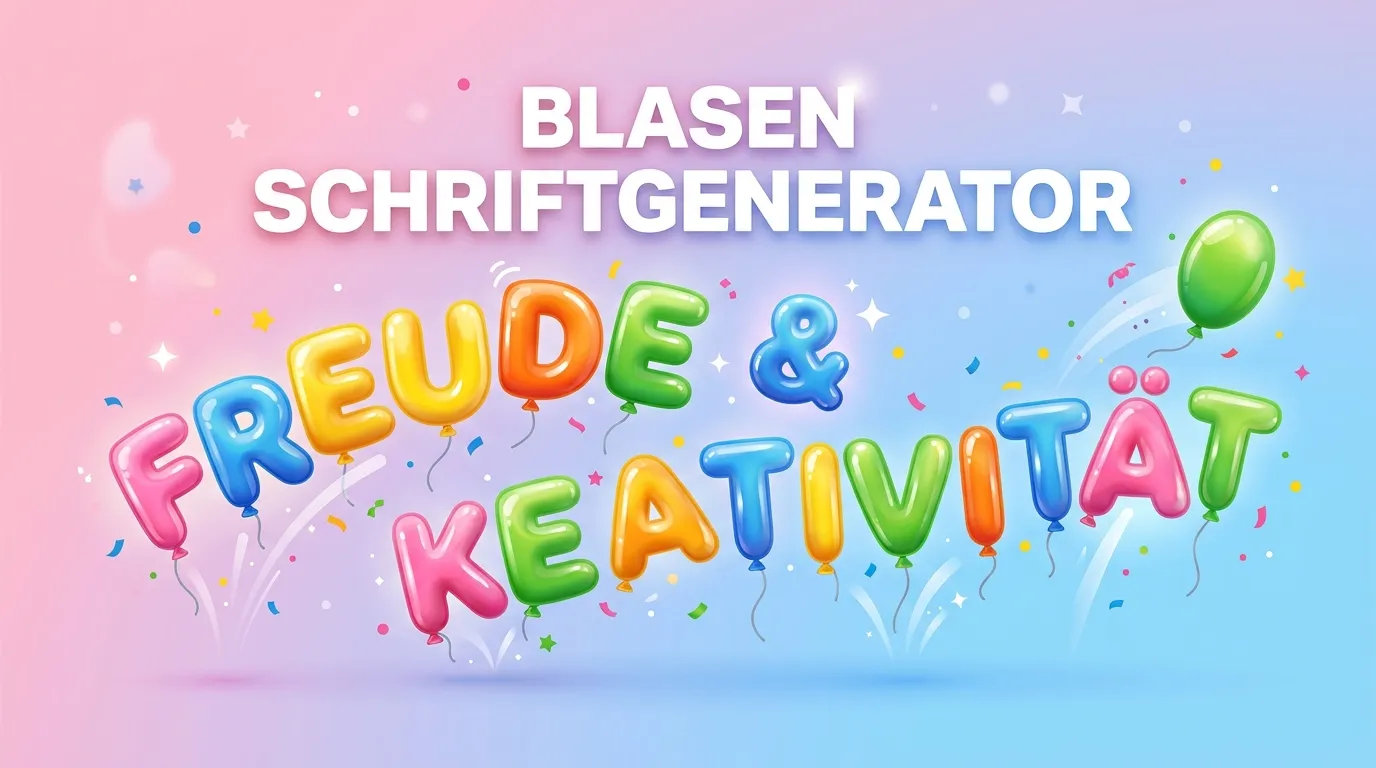
Blasen Schriftgenerator
Erstelle verspielte Bubble-Text-Schriften mit eingekreisten und umrahmten Buchstaben. Perfekt für Instagram-Bios, TikTok-Profile und kreative Posts. Kostenlos, ohne Anmeldung, direkt im Browser.
Hinweis: Umlaute (ä, ö, ü, ß)
Deutsche Umlaute und ß haben keine Blasen-Entsprechung im Unicode-Standard und erscheinen daher in normaler Schrift neben den umgewandelten Buchstaben. Das ist eine unvermeidliche technische Einschränkung aller Blasen-Generatoren, nicht ein Fehler unseres Tools.
Barrierefreiheit: Unicode-Sonderzeichen werden von Screenreadern (VoiceOver, TalkBack) oft nicht korrekt vorgelesen. Für zugängliche Websites empfehlen wir semantisches HTML-Formatting statt Unicode-Zeichen.
Bubble Text für Instagram und TikTok
Blasen-Schrift ist eine der beliebtesten Schriftstil-Optionen auf Instagram und TikTok, weil sie gleichzeitig verspielt, lesbar und auffällig ist. Eingekreiste Buchstaben (Ⓐ, ⓑ, Ⓒ) erzeugen eine retro-comic-artige Ästhetik, die in algorithmisch optimierten Feeds sofort ins Auge fällt.
Viele Creator verwenden Blasen-Schrift für Kategorie-Labels in der Bio ("📍 Ⓓⓔⓤⓣⓢⓒⓗⓛⓐⓝⓓ"), Abschnittstrennungen oder als visuell einheitliches Namensschild.
Technischer Hintergrund: Unicode Enclosed Alphanumerics
Blasen-Buchstaben stammen aus dem Unicode-Block "Enclosed Alphanumeric Supplement" (U+1F150-U+1F189 für gefüllte Formen und U+24B6-U+24E9 für einfache Kreise). Diese Zeichen sind speziell für visuelle/dekorative Zwecke in den Unicode-Standard aufgenommen worden.
Da es sich um reguläre Unicode-Zeichen handelt, werden sie von allen modernen Betriebssystemen und Plattformen unterstützt. Zuletzt aktualisiert: August 2026
Was ist Blasen-Schrift (Bubble Text)?
Blasen-Schrift (englisch: Bubble Text) bezeichnet Buchstaben, die in Kreisen oder anderen geometrischen Formen eingebettet sind: zum Beispiel Ⓐ, ⓑ, 🅒. Technisch handelt es sich um Unicode-Zeichen aus dem "Enclosed Alphanumeric"-Block, der extra für solche visuellen Effekte geschaffen wurde.
Auf welchen Plattformen funktioniert Blasen-Text?
Blasen-Text funktioniert hervorragend auf Instagram, TikTok, WhatsApp, Discord und Facebook. Die eingekreisten Zeichen sind gut im Unicode-Standard verankert und werden auf praktisch allen modernen Geräten korrekt dargestellt.
Warum fehlen manche Umlaute in der Blasen-Schrift?
Der Unicode-Enclosed-Alphanumeric-Block enthält nur die 26 Grundbuchstaben (A-Z) und Ziffern (0-9). Für deutsche Umlaute (ä, ö, ü, ß) gibt es keine Blasen-Variante im Unicode-Standard. Sie erscheinen daher im Originalstil neben den Blasen-Buchstaben.